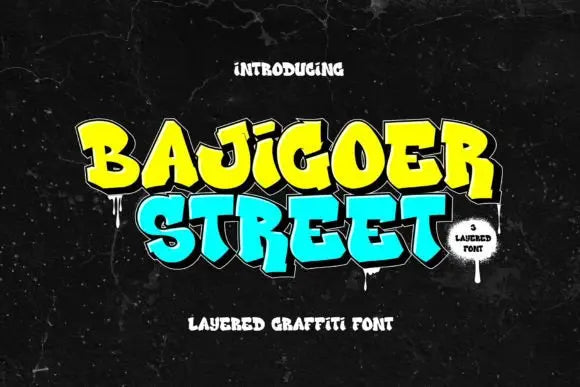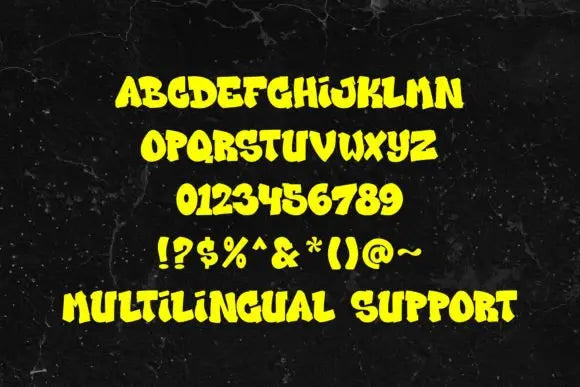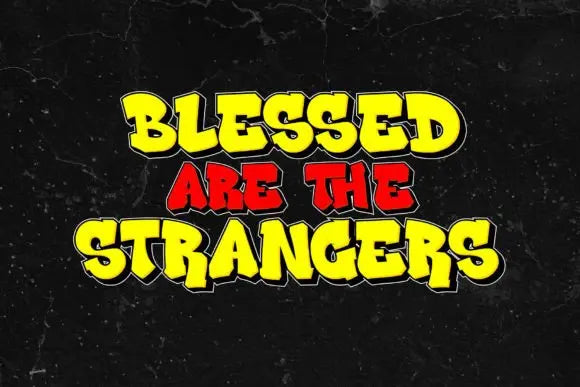
Fuente Bajigoer Street
Sumérgete en el ambiente urbano con Bajigoer Street, una sorprendente fuente de graffiti en capas en 3D. Caracterizada por tres estilos distintos: sólido, sombra interior y sombra exterior, esta fuente da una impresión de dinamismo y profundidad a su texto, agregando un toque único a sus diseños.
El estilo sólido tiene que ver con ser audaz e inequívoco, mientras que los estilos de sombra interior y exterior infunden al texto una sensación de profundidad, cargándolo con el atractivo de un efecto tridimensional y de sombra.
Ideal para aquellas tareas inspiradas en el arte callejero, carteles llamativos o cualquier proyecto de diseño que anhele una tipografía atrevida y en capas, Bajigoer Street es su fuente ideal para grabar una impresión.